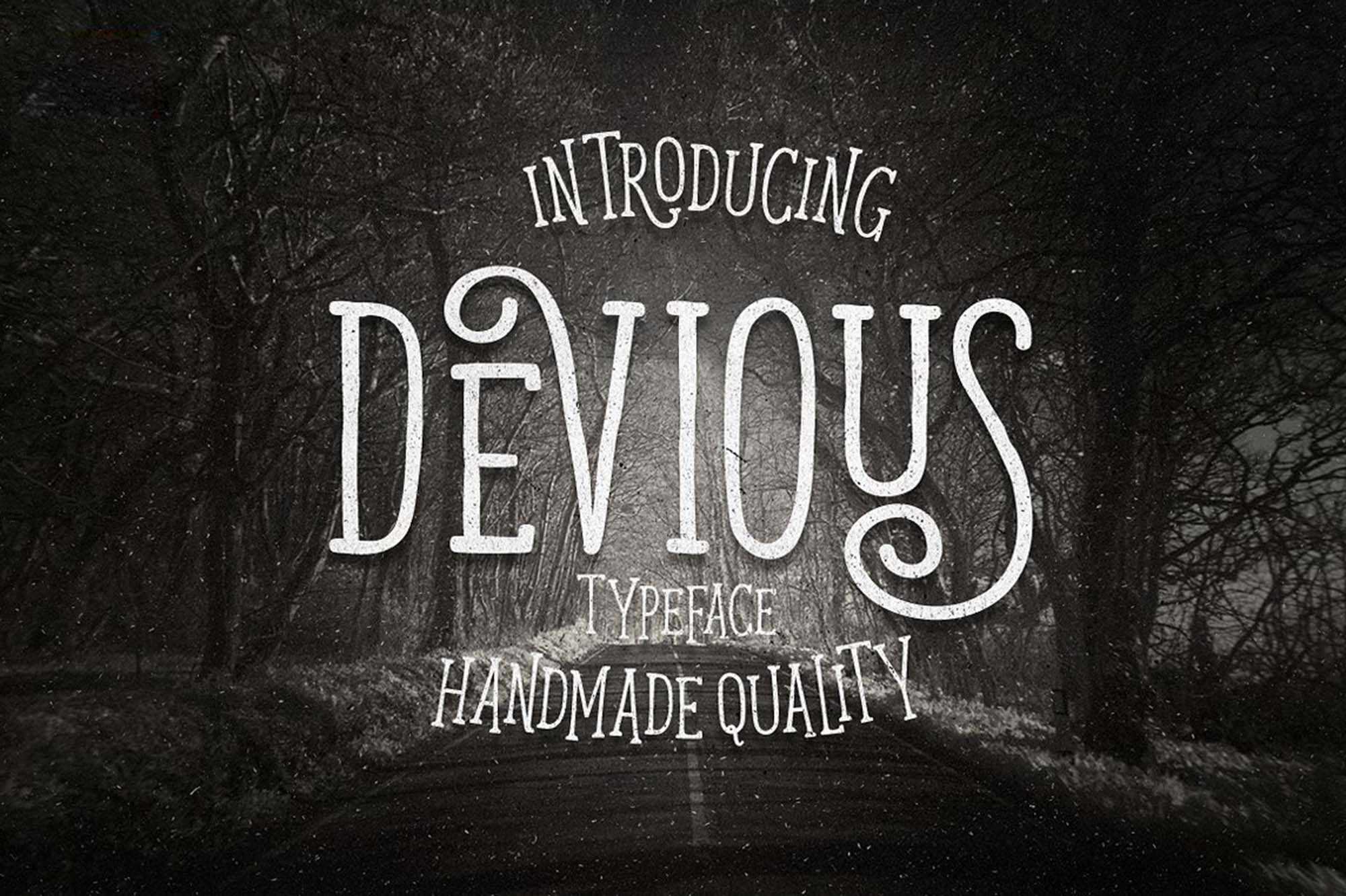
Devious Retro Typeface
Imagine uma página de download para um tipo de font retrô chamado Devious Retro Typeface. Se a gatinha misteriosa Cheshire decidisse partir do mágico e desconhecido mundo de Alice para se instalar em nossa realidade, ela provavelmente escolheria este tipo de font para usar. Sua elegância vintage e sutileza iriam ser perfeitas para uma carreira como escritor anônimo. Com seu design arredondado e linhas finas, Devious Retro traz um toque enigmático e sofisticado para qualquer projeto de design gráfico. Seja para criar um logo de editora de gibis, um título para uma revista de moda, ou uma capa para um álbum de música, esta font oferece um toque de modernidade e charme retrô que certamente destacará seu trabalho. Ideal para designers que buscam algo que seja tanto um recurso para sua estética como uma fonte de inspiração, Devious Retro é um recurso gráfico que não pode faltar no seu banco de recursos.